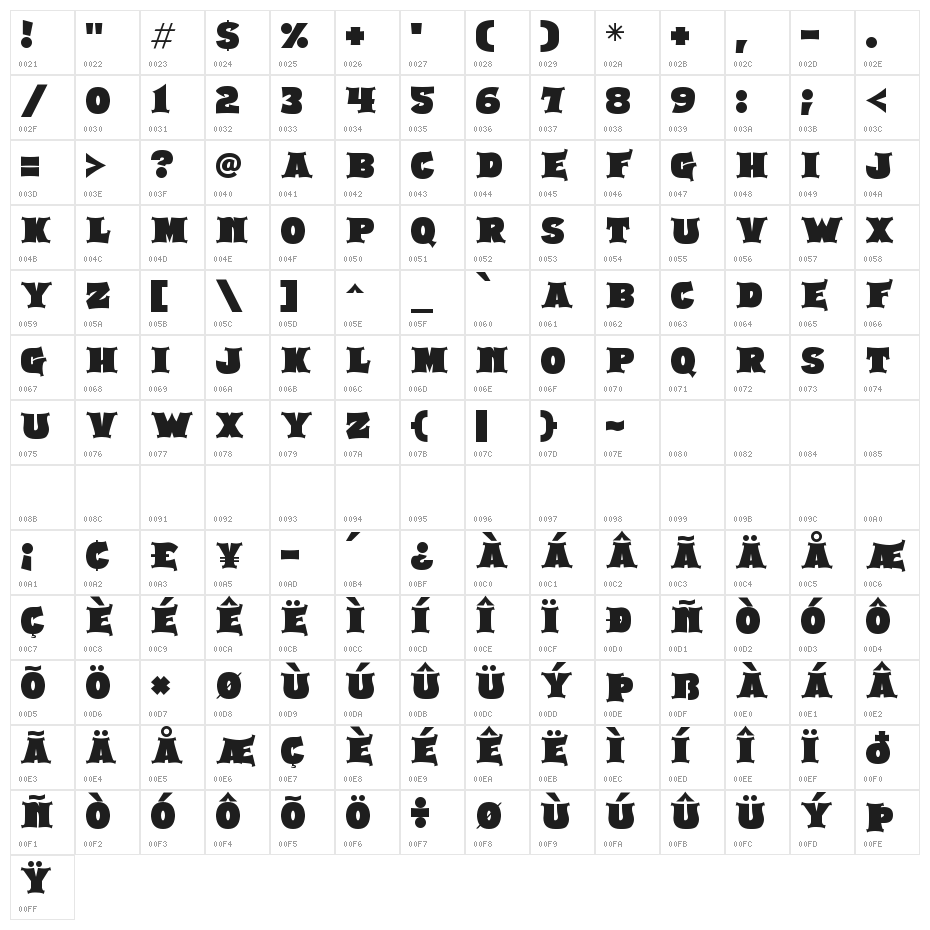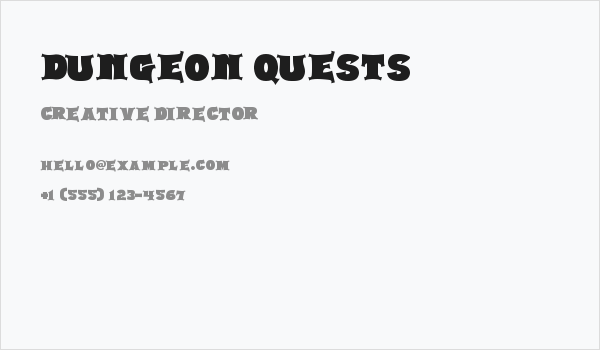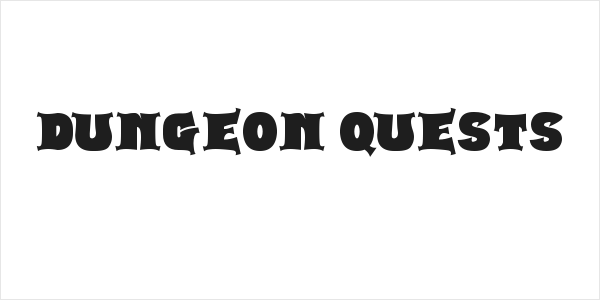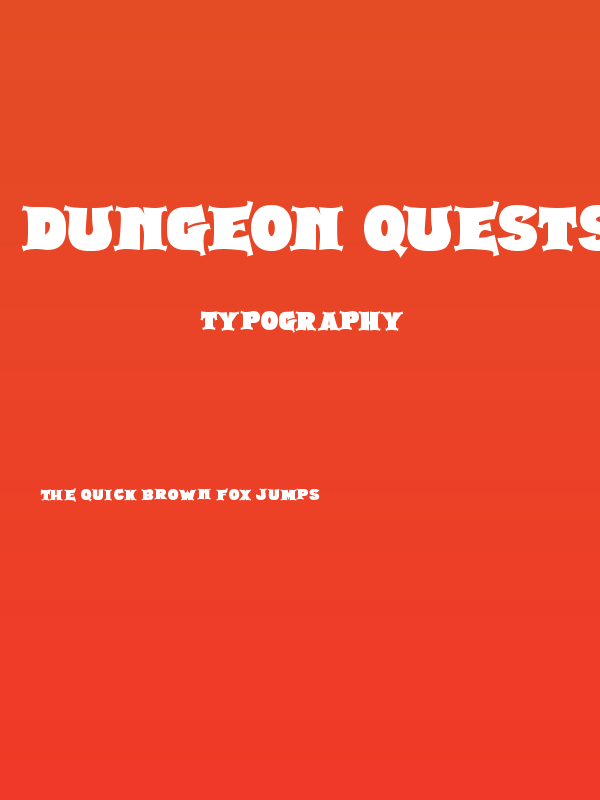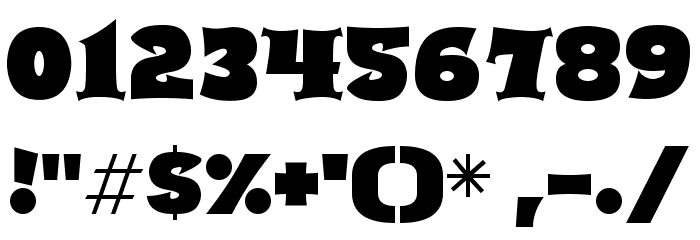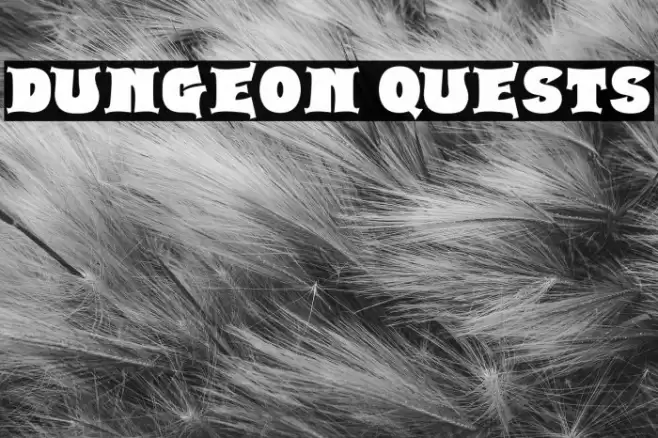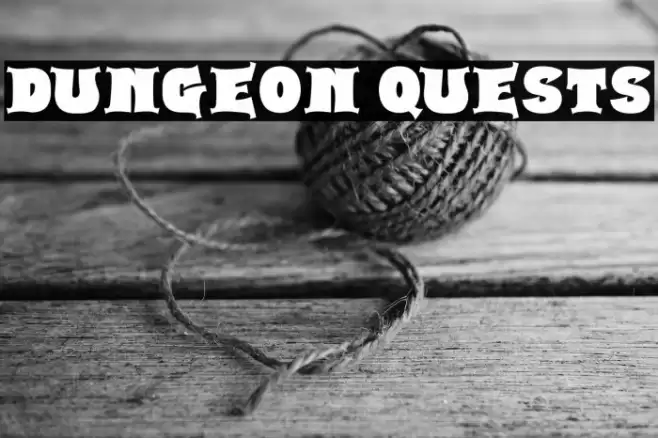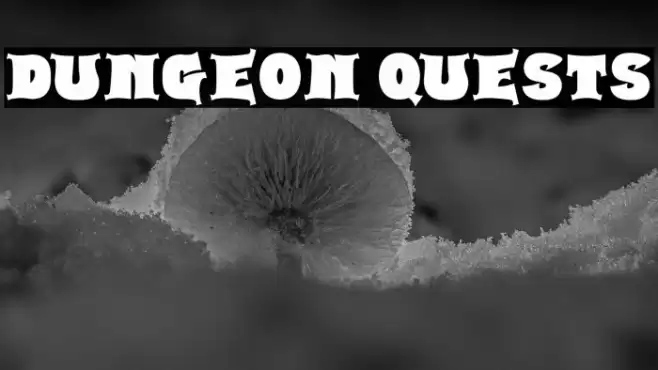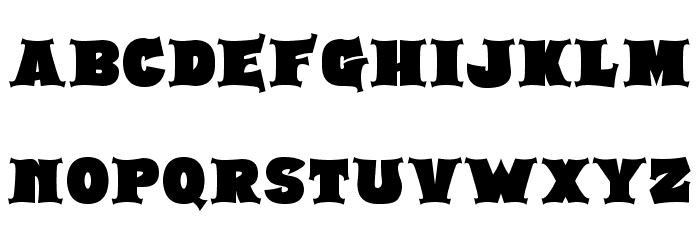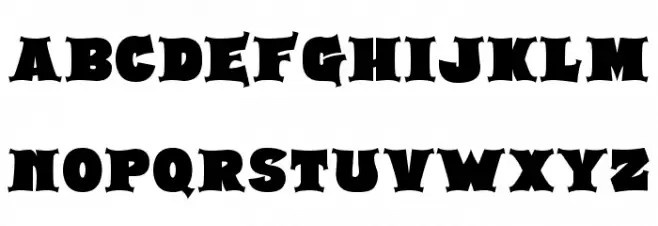
Dungeon Quests Font
| Projetos propostos | Ideal for fantasy-themed games, book covers, posters, and branding that requires a dramatic and adventurous look. |